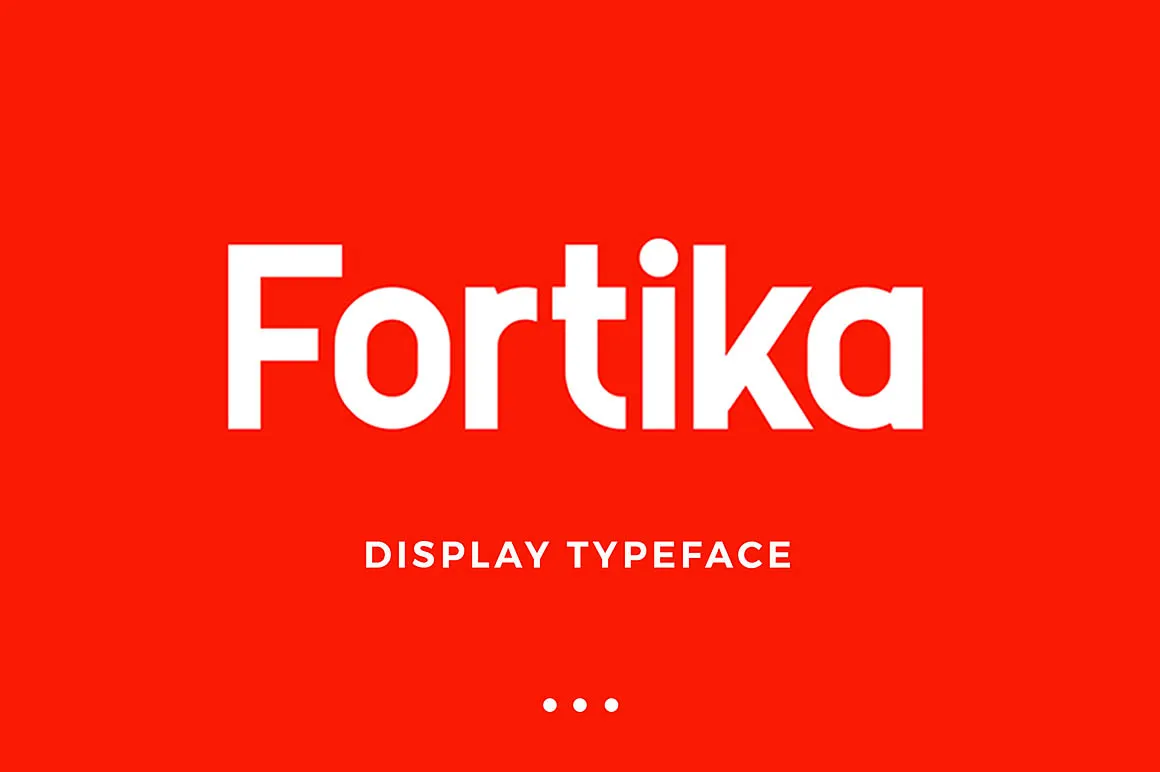
Fortika™ Display Typeface – Download Grátis
Fortika™ Display Typeface é uma tipografia sans serif geometrica criada por Deni Anggara, um designer alemão de Berlim. Esta fonte exibe linhas fortes e linhas limpas que tornam-a ainda mais bela quando usada em grandes tamanhos. Inspirado no estilo moderno, jovem espírito e design gráfico casual das marcas esportivas, como Nike, New Balance e Adidas, Fortika Display está disponível com letras maiúsculas e minúsculas, números e sinais de pontuação, incluindo alguns glyphes alterados para um resultado mais atraente. É perfeita tanto para aplicações digitais quanto impressão, oferecendo um estilo moderno e sofisticado que se adequa a diversas necessidades de design gráfico.